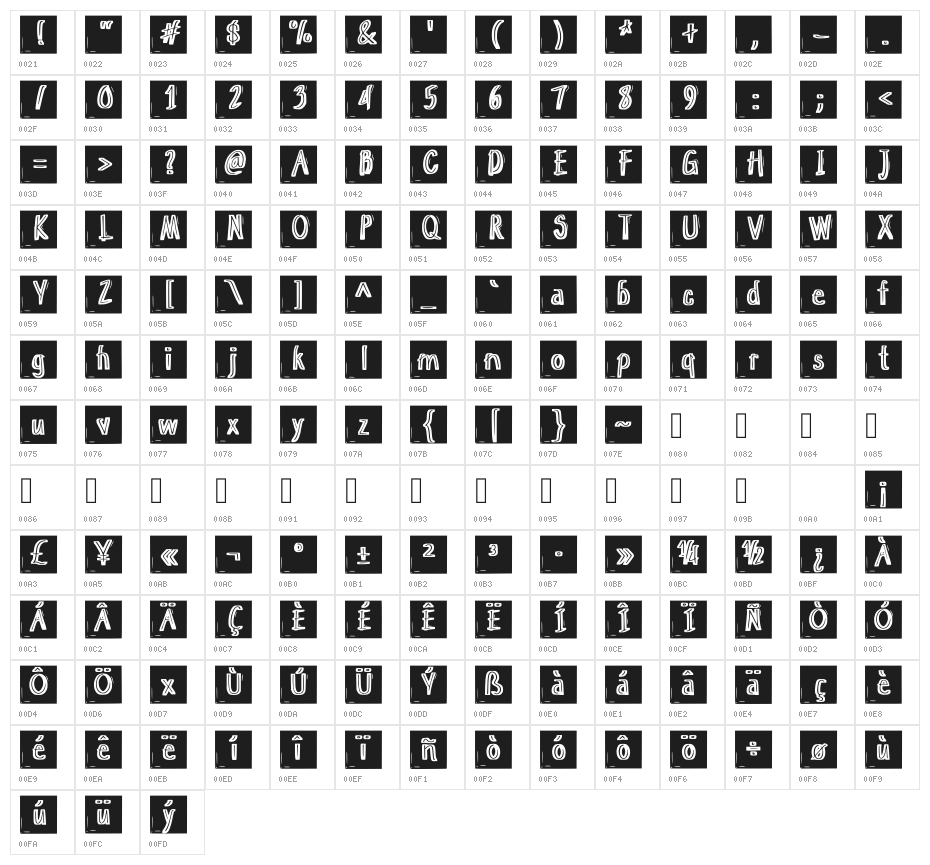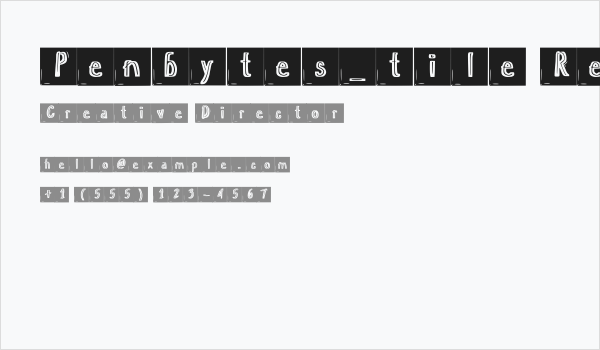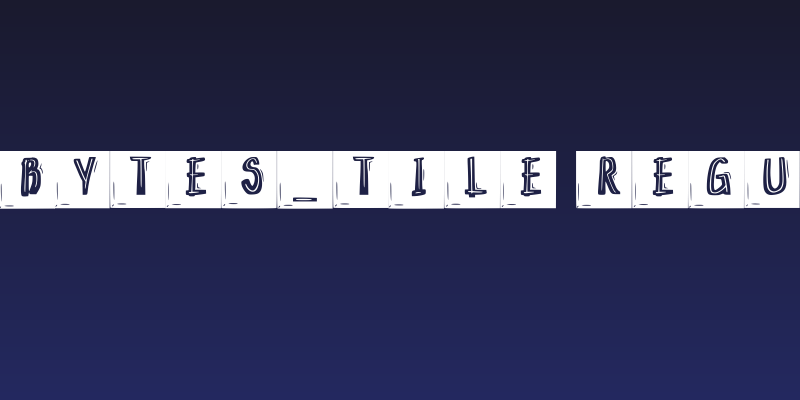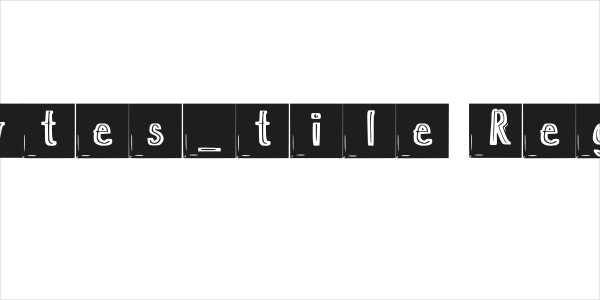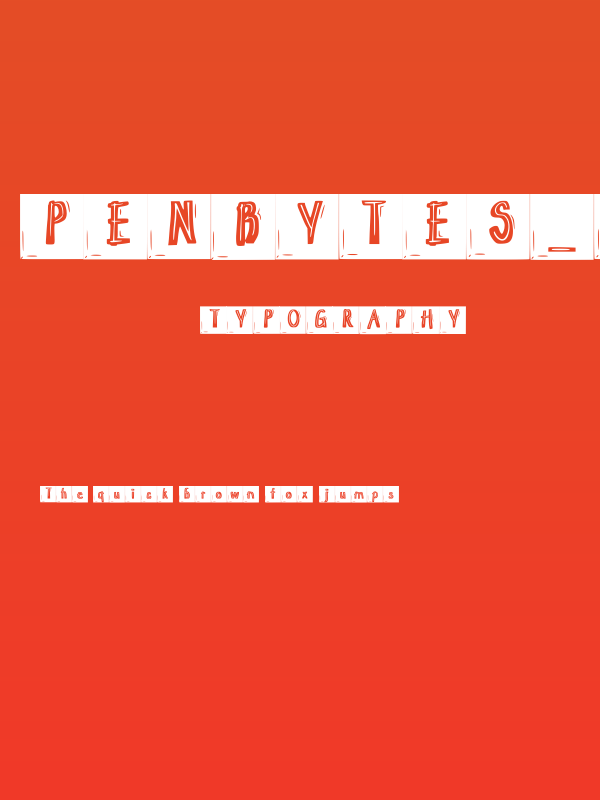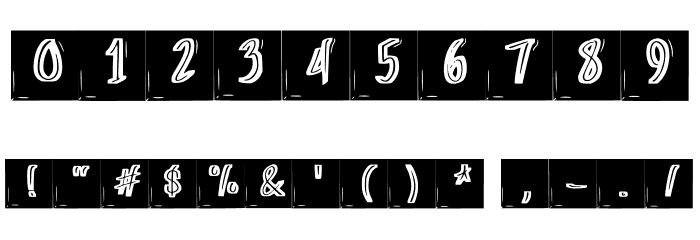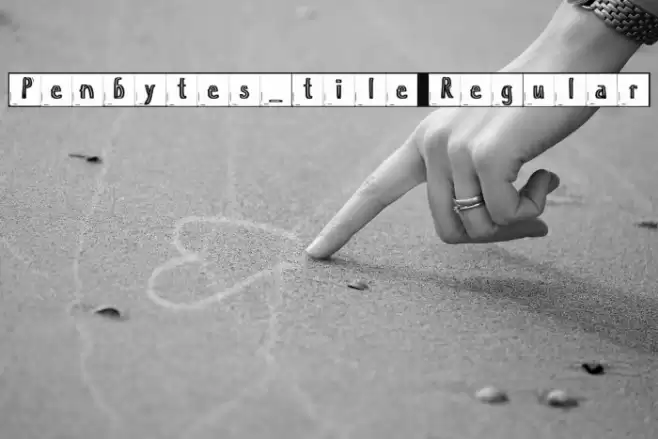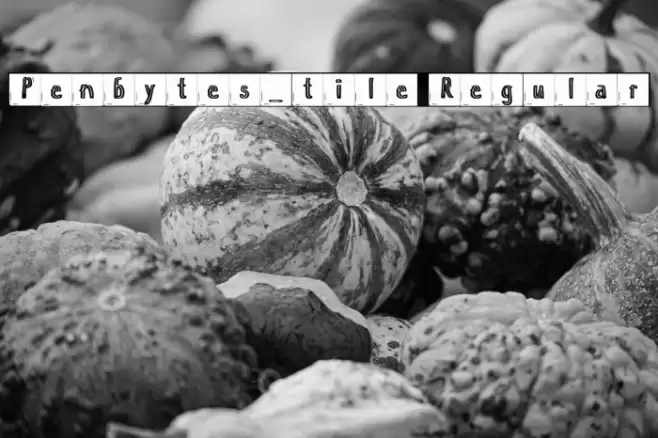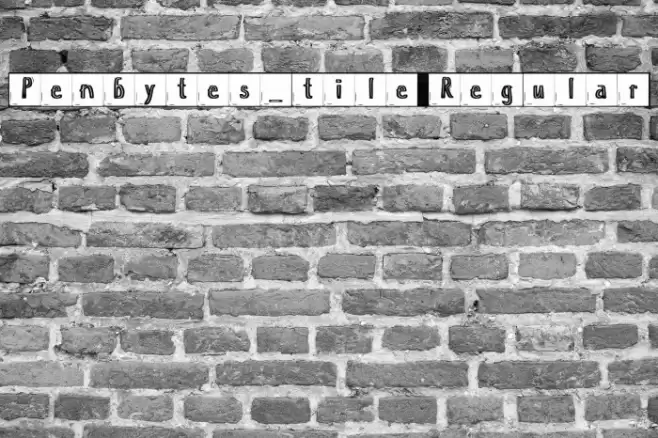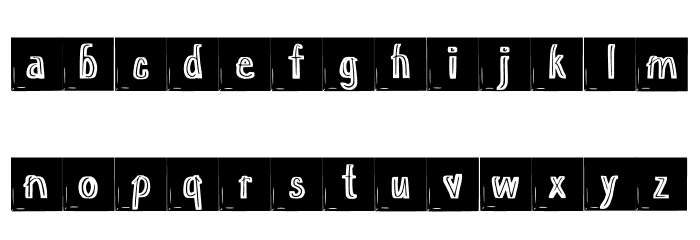
Penbytes_tile Regular Font
✎ Decorative
| 分类 | Decorative |
| 整体风格 | Playful, Quirky, Hand-drawn |
| 使用场景 | Headlines, Logos, Informal Text |
| 推荐项目 | Ideal for children's books, comic strips, casual invitations, and playful branding. |